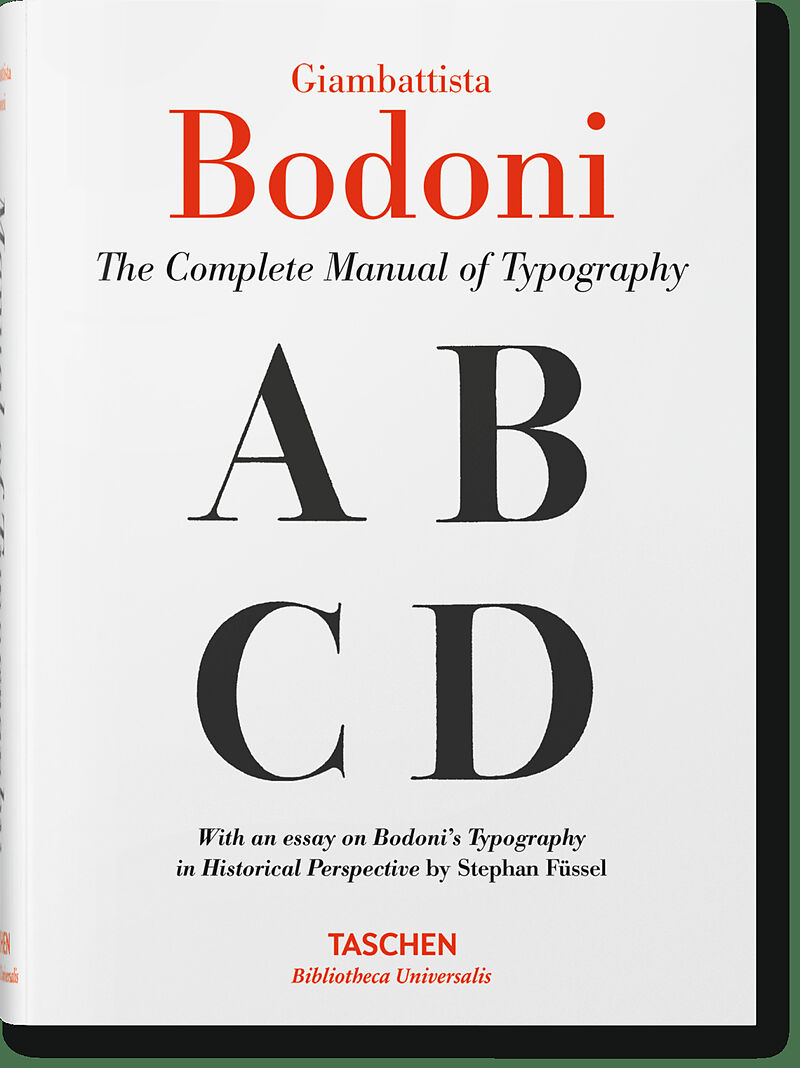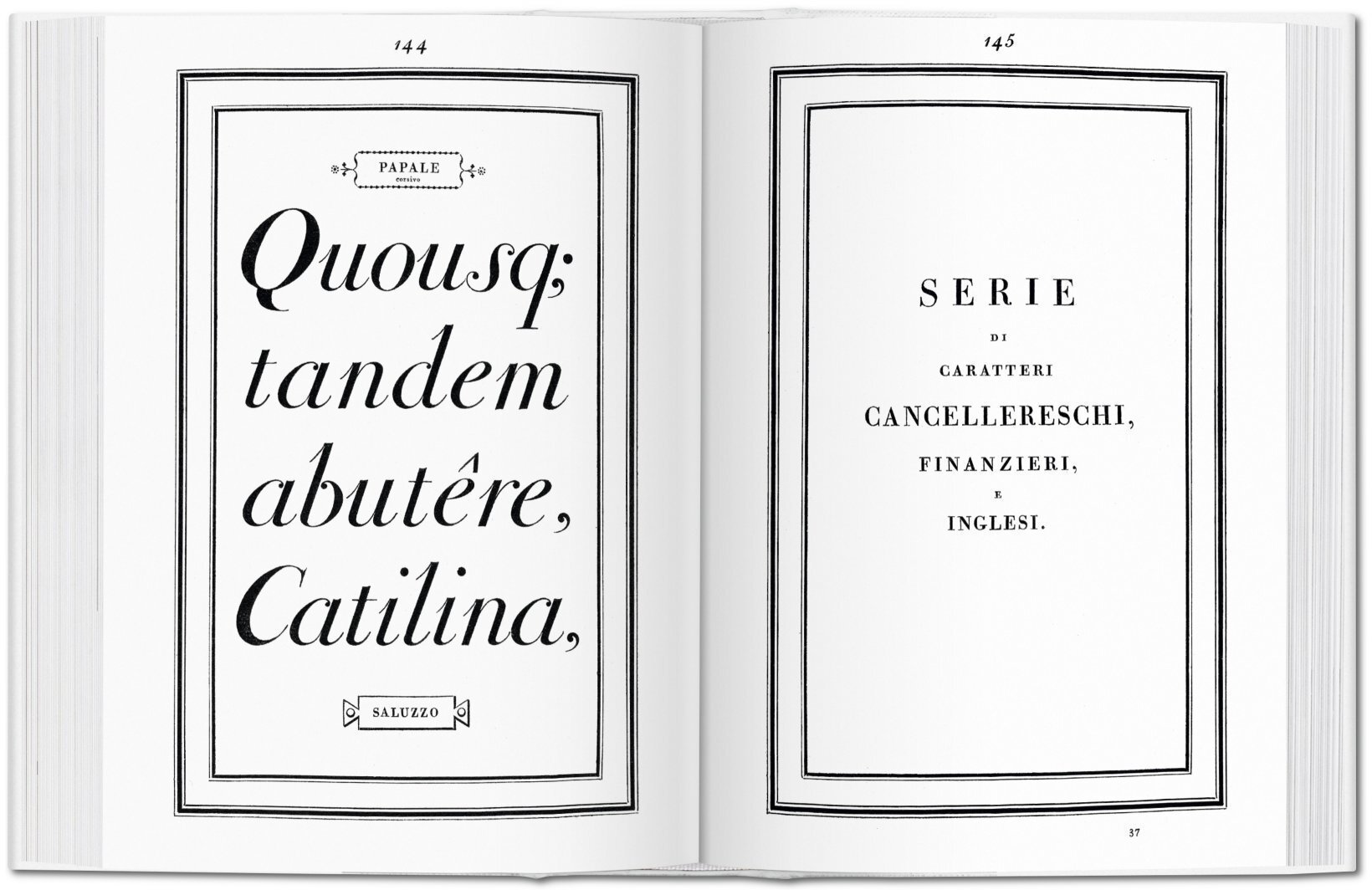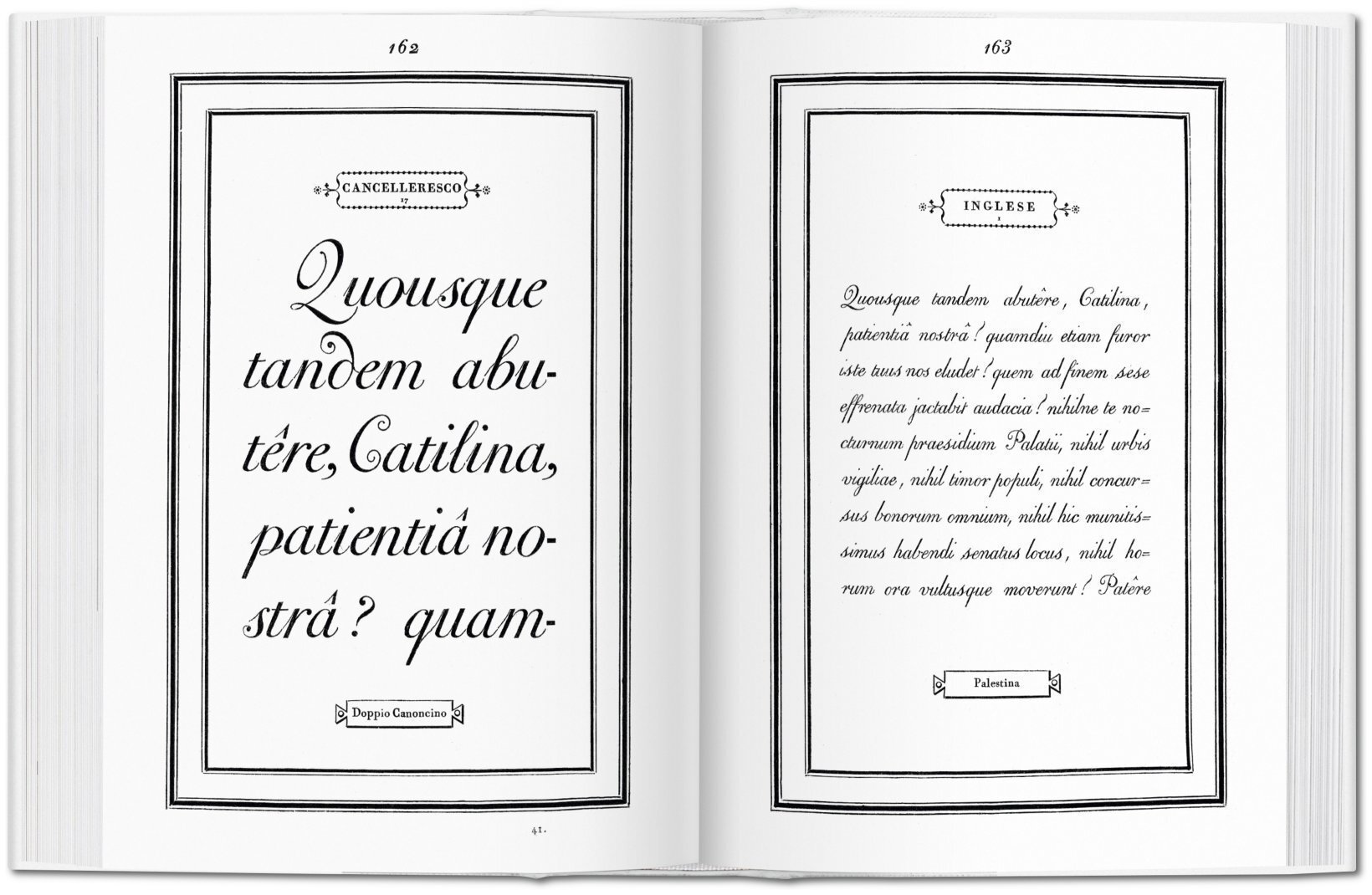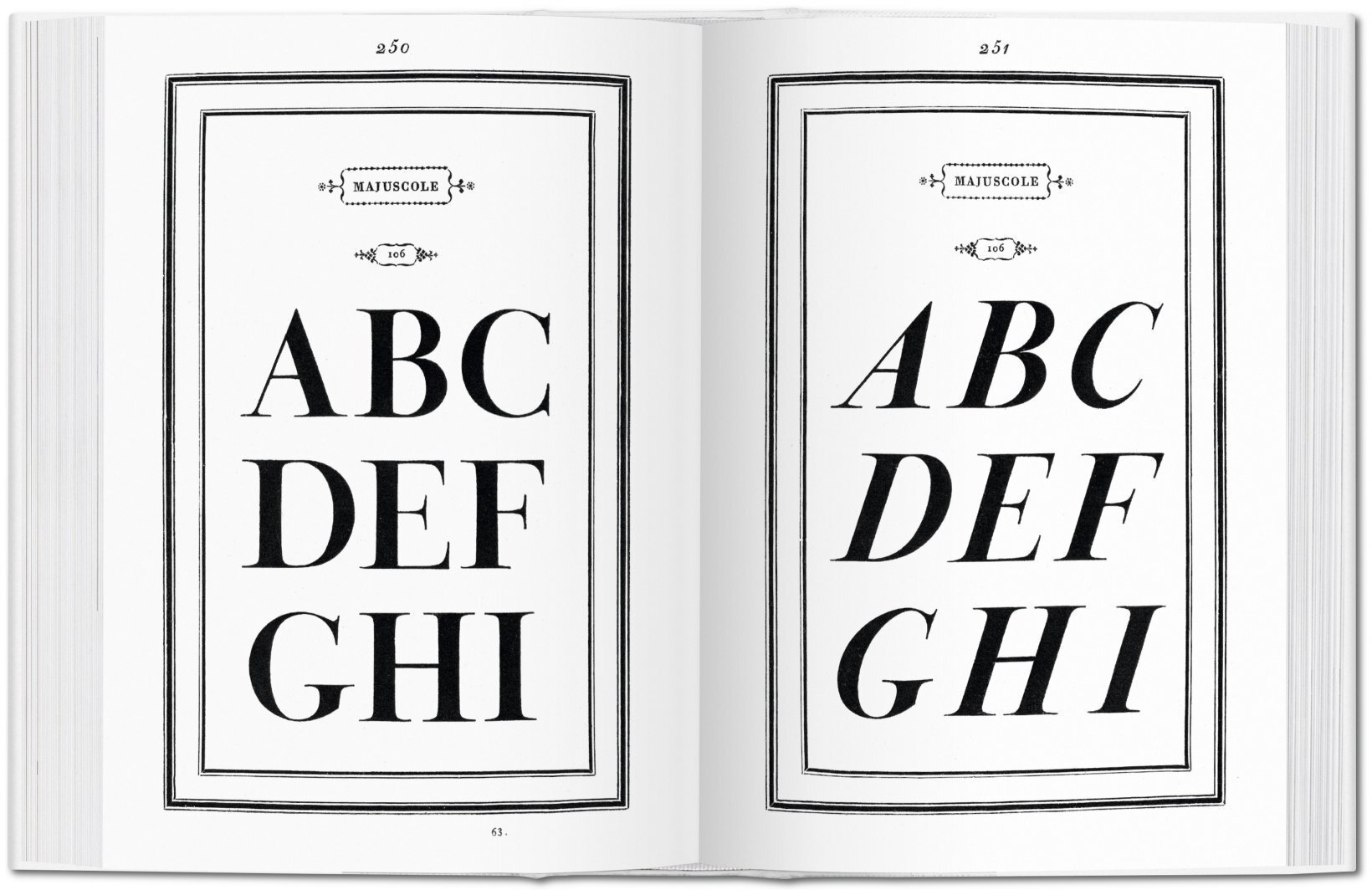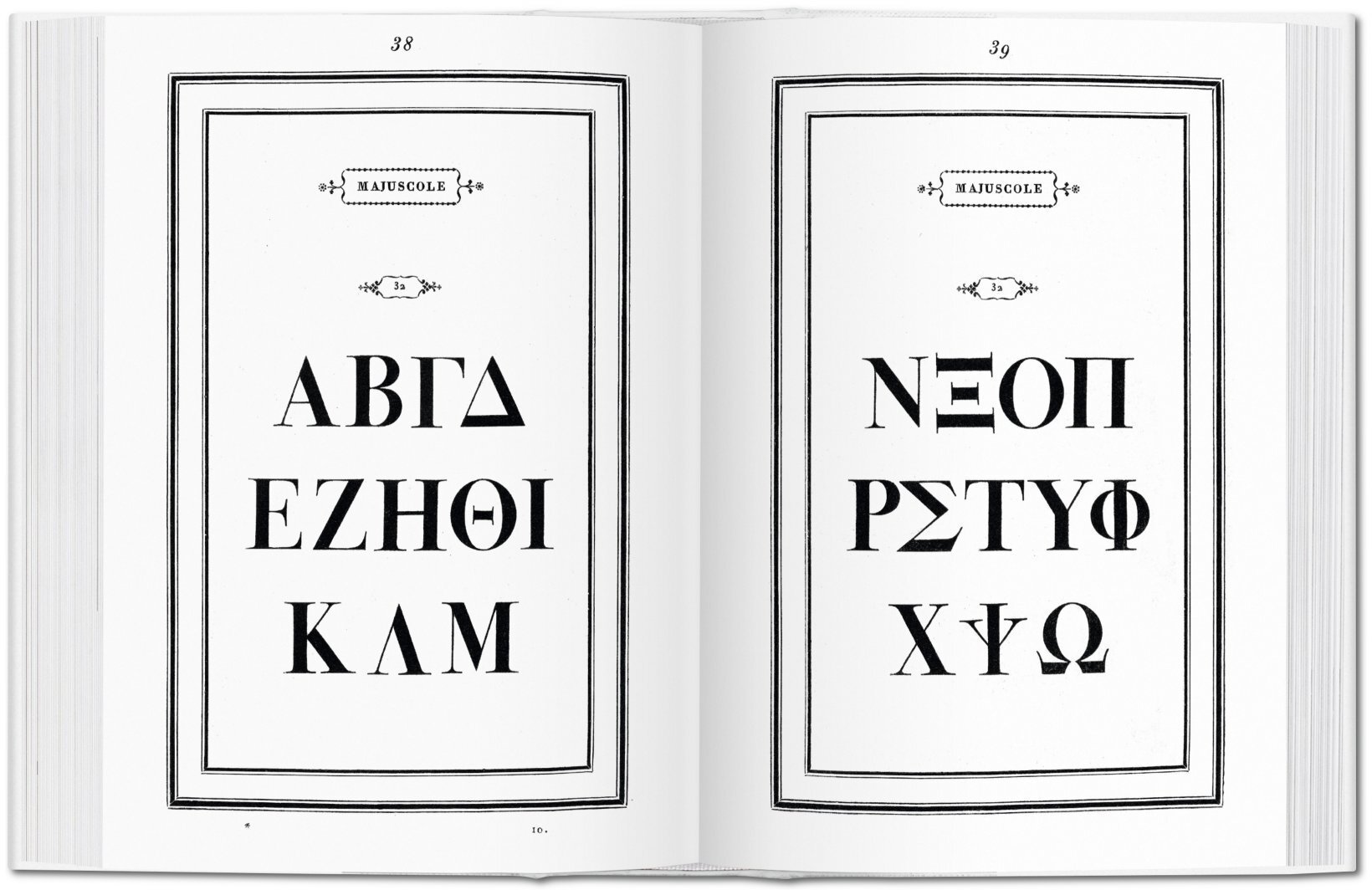
Giambattista Bodoni. Das vollständige Handbuch der Typografie
Auch rund 200 Jahre nach seinem Tod bestechen die von Giambattista Bodoni entworfenen Antiquaschriften durch kühle Eleganz und klassizistische Formstrenge. Die Bilanz seines Lebenswerkes, das Manuale tipografico von 1818, unterstreicht Bodonis herausragende Be...